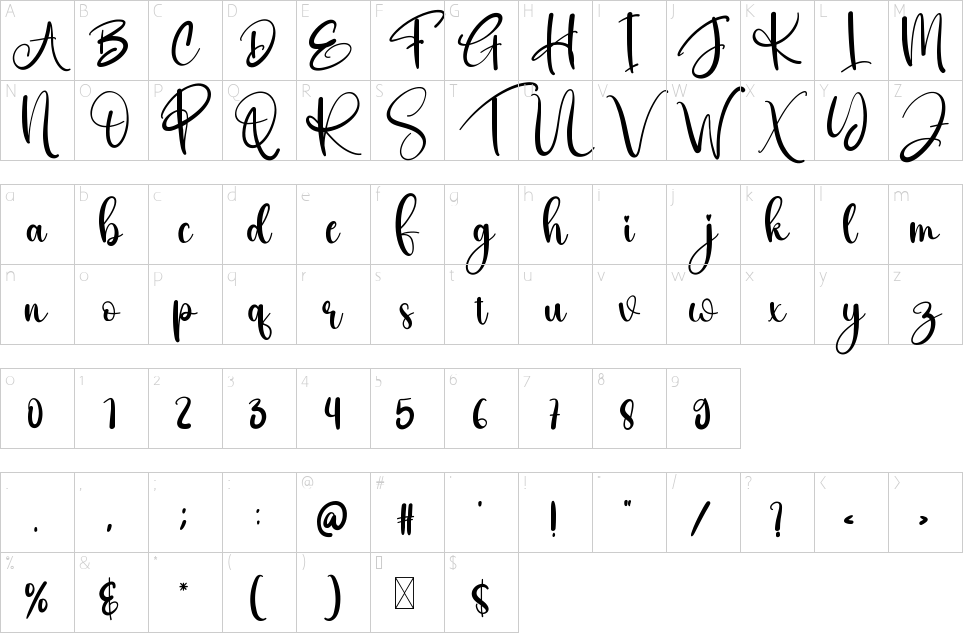
A Girly Font é uma elegante e divertida escolha para quem busca estilizar textos de forma única e pessoal. Desenhada por scratchones, essa fonte foi popular entre os fãs graças à sua simplicidade e encanto irresistível. Com a Girly Font, você pode adicionar um toque delicado aos seus projetos gráficos, seja para criar uma identidade visual mais jovem e descontraída ou simplesmente dar um ar especial aos textos de seu site ou aplicativo. Com download fácil tanto no Windows quanto na versão Mac, a Girly Font é uma ótima opção para designers que buscam recursos gratuitos com grande potencial criativo. Desde nomes para estilos básicos até criações mais elaboradas, essa fonte traz um toque autêntico e divertido às suas produções digitais.